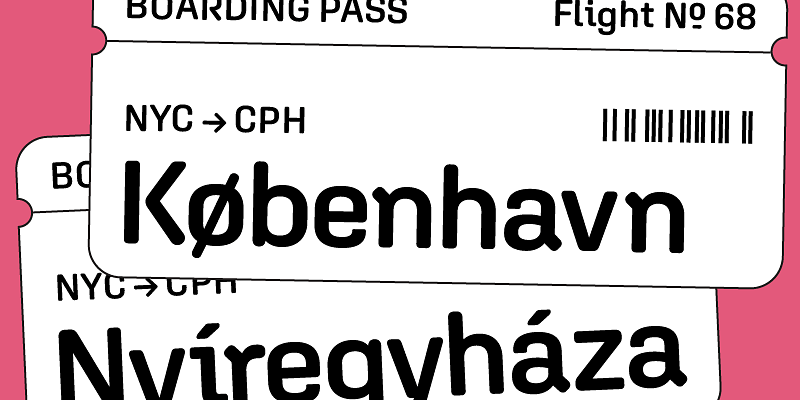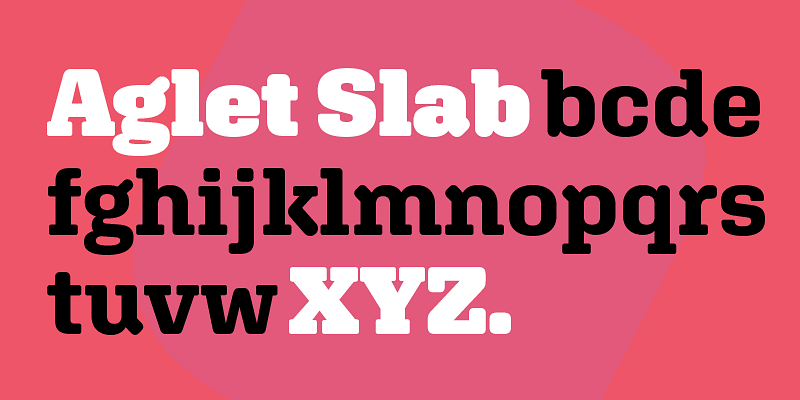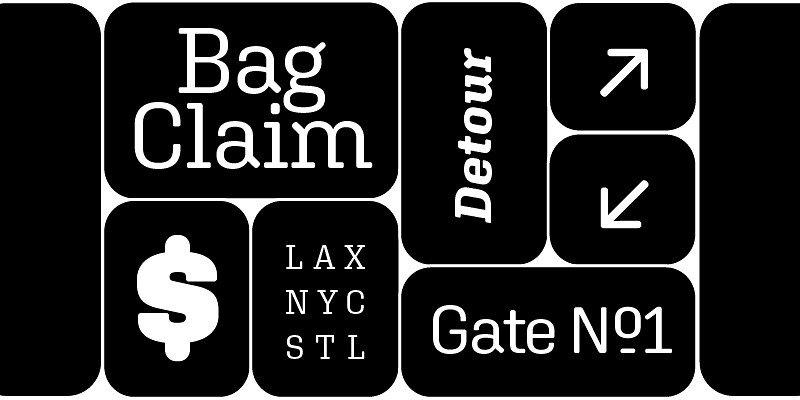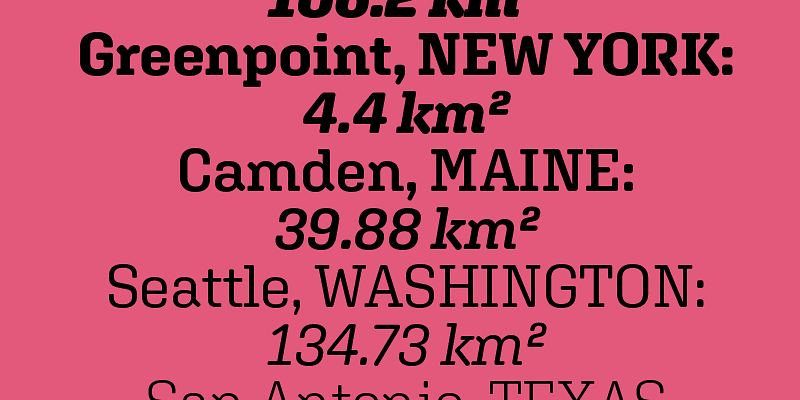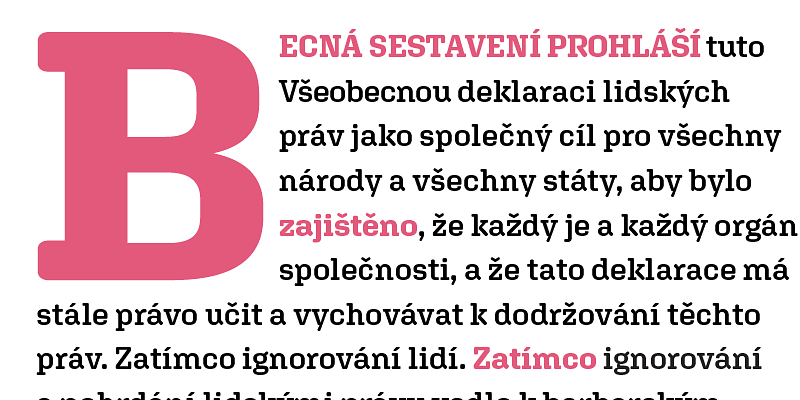
Rundhed er hjertet i Aglet Slabs’ struktur – ikke kun en overfladedetalje. Stumpe seriffer og gentagne geometriske former finder variation i et strategisk hierarki af kurver, fra subtilt polstrede punkter til bratte cirkulære ender. En underliggende struktur med 45° og 90° vinkler giver et stabilt grundlag for mere stolte karakterer og organiske detaljer.
Aglet Slab genlyder af en venlig højteknologisk tone, når den bruges fremtrædende, men den forbliver sprød og smidig i længere tekster. En bred vifte af vægte i latinsk og kursiv tilføjer op til fjorten alsidige stilarter, hver med matchende symboler. Du vil have Aglet Slab lige ved hånden, uanset hvad du løber ind i.
Ben Kiel og Jesse Ragan laver brugbare og underspillet spøjse skrifttyper via deres uafhængige digitale designstudie, XYZ Type, som opererer i underskoven mellem St. Louis og New York. Efter at have ansat hinanden skiftevis og nået frem til, at de arbejdede godt sammen, startede makkerparret XYZ Type i 2017 for at forene deres respektive styrker og brede erfaring inden for skrifttypedesign og bogstavdesign for store brands, kulturinstitutioner og publikationer.
Deres speciallavede projekter og projekter for detailkunder forstærker hinanden indbyrdes – nogle tager form som kundebestilte opgaver, mens andre er spekulative designs, som Ben og Jesse mener vil passe ind i en kommerciel niche. XYZ Type tegner originale skrifttyper og logotekst fra bunden, tilpasser versioner af deres detailskrifttyper for at skræddersy dem til en kundes specifikke behov og finpudser skitser af kunders logotekster. De trives med at samarbejde med mennesker, der er lige så vilde med skrifttyper, som de selv er.
Ben og Jesse henter energi fra historien, folkeligt bogstavdesign og uortodokst grafisk design, og de jagter nye idéer til skrifttyper, som er lige så udspekulerede, som de er teknologisk robuste. Deres minutiøse udviklingsproces fører dem ofte i overraskende retninger, som giver dem de små, men væsentlige øjeblikke, hvor de opdager noget helt nyt – og det gør XYZ Types designs helt unikke.